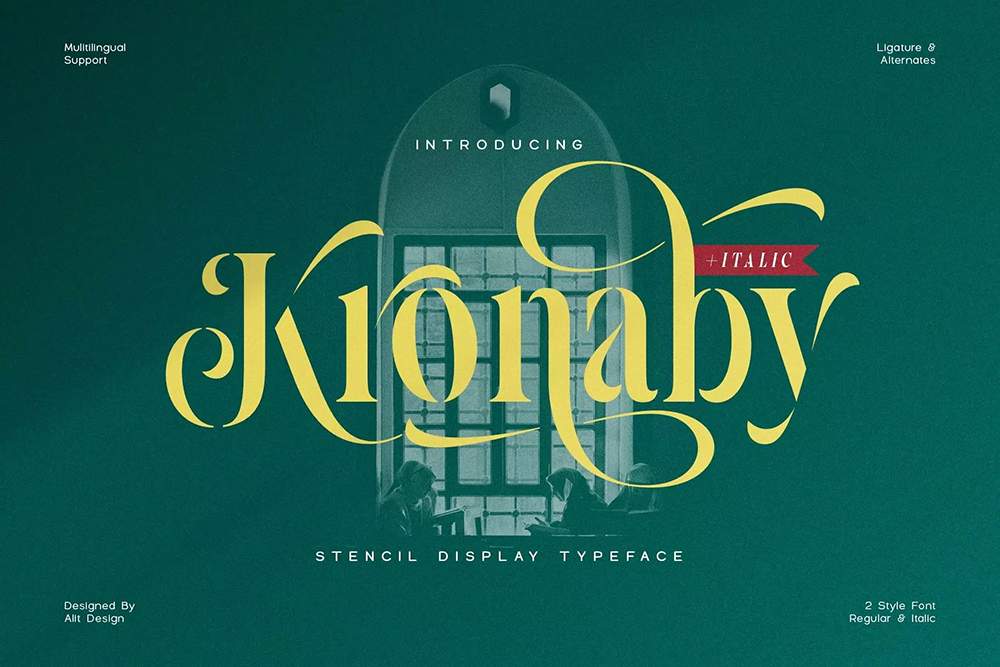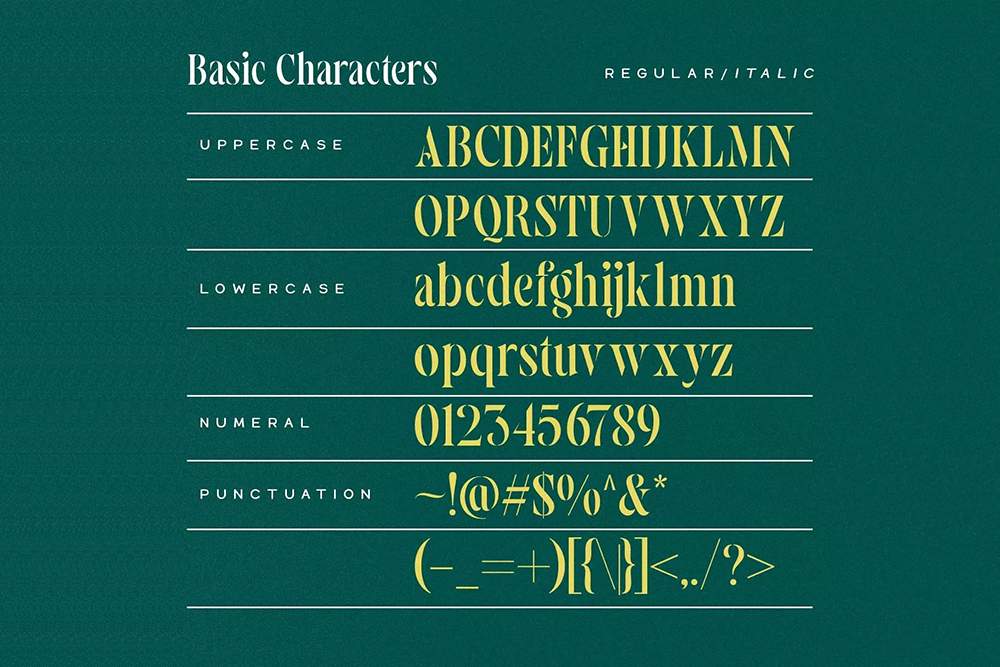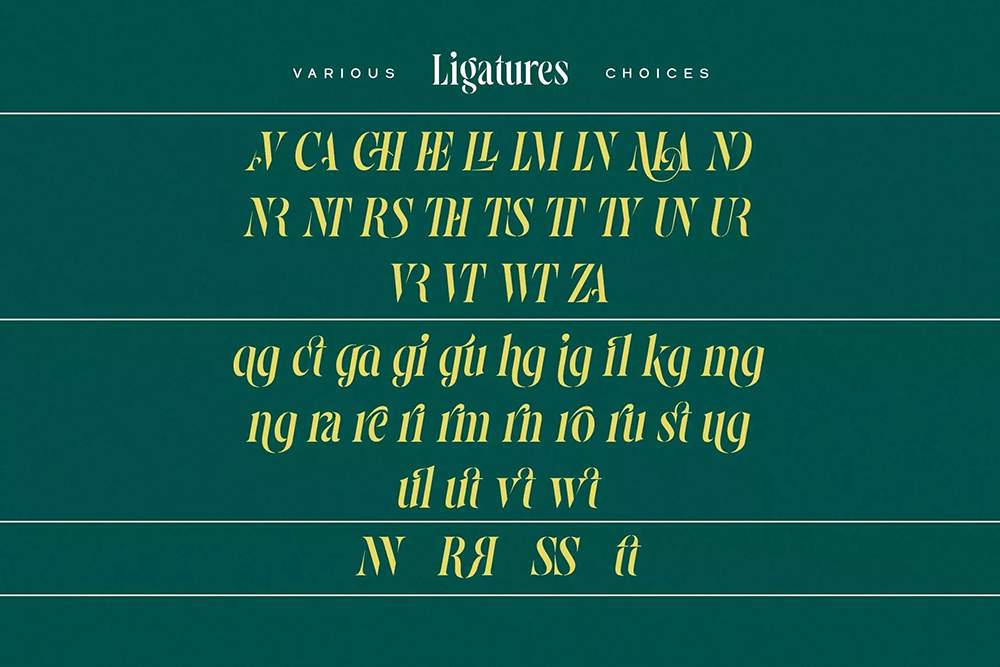
دانلود فونت انگلیسی Kronaby Font
فونت پرمیوم و انگلیسی Kronaby Font یک سبک استنسیل زیبا و جذاب برای یک طراحی مدرن، همراه با یک سواش ظریف است. علاوه بر سواش در فونت Kronaby، شکلهای کاراکتر جایگزین و لیگاتورهای منحصر به فرد Discreationary نیز وجود دارد. فونت “Kronaby” به راحتی در هر طرحی، به ویژه طرحهایی با ظاهری زیبا، مدرن و کلاسیک، قابل استفاده هست. Kronaby شامل 756 حروف با گزینههای جایگزین منحصر به فرد و جالب بسیاری است. علاوه بر فونت معمولی، یک نسخه ایتالیک از فونت Kronaby نیز وجود دارد.
مزایای استفاده از فونت لاتین Kronabyچیست؟